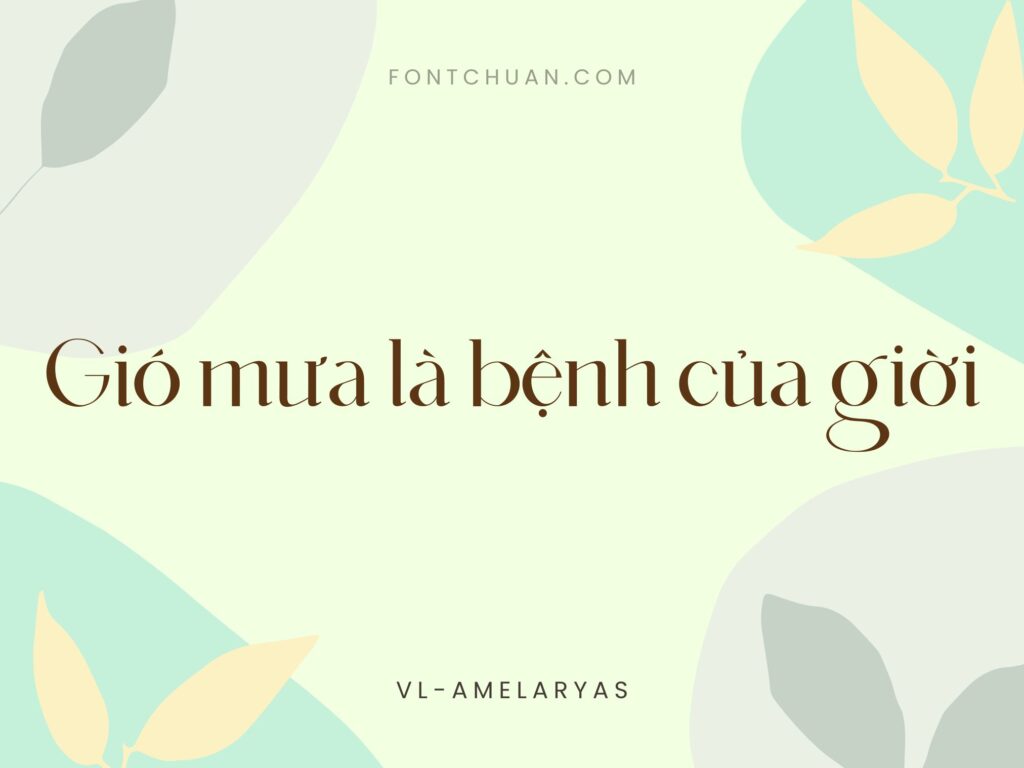
Font VL Amelaryas Việt Hóa
Tác giả Font: Hishand Studio
Việt hóa bởi: Font Việt Linh
VL-Amelaryas là một phông chữ serif mang phong cách sang trọng và tinh tế, được thiết kế bởi Hishand Studio. Với các đường nét thanh thoát và chân chữ tinh tế, phông chữ này tạo nên sự đẳng cấp và trang nhã cho các thiết kế.
Phông chữ này đã được Việt hóa bởi Việt Linh, hỗ trợ đầy đủ các ký tự tiếng Việt, giúp người dùng dễ dàng sử dụng trong các dự án sáng tạo. VL-Amelaryas được thành viên Font Chuẩn sưu tầm và đăng tải nhằm phục vụ nhu cầu thiết kế đa dạng.
Với thiết kế thanh lịch và rõ ràng, VL-Amelaryas phù hợp cho các ứng dụng như tiêu đề, văn bản dài, thiết kế logo và các ấn phẩm in ấn. Trong lĩnh vực sự kiện, phông chữ này có thể được sử dụng trong các dịp như hội nghị, lễ kỷ niệm và các sự kiện văn hóa. Ngoài ra, VL-Amelaryas cũng thích hợp cho các ngành nghề như xuất bản, giáo dục và truyền thông.